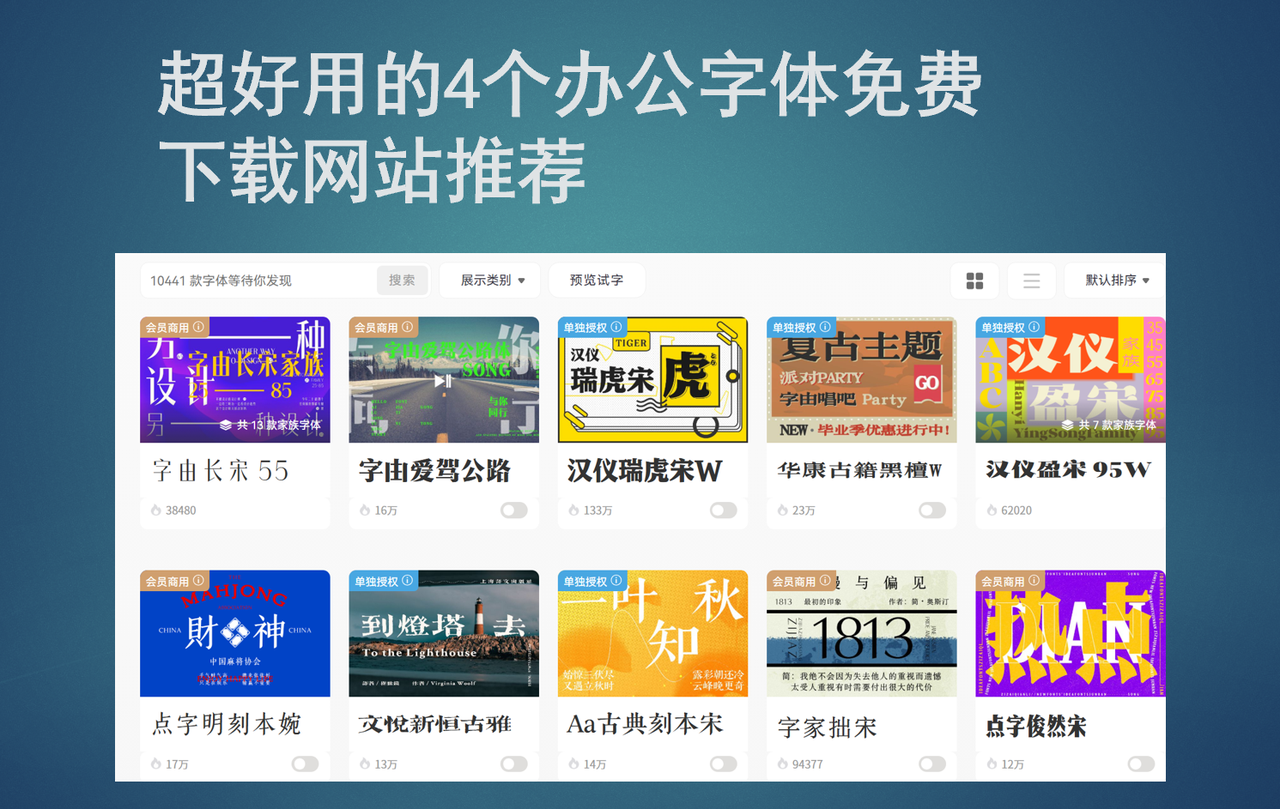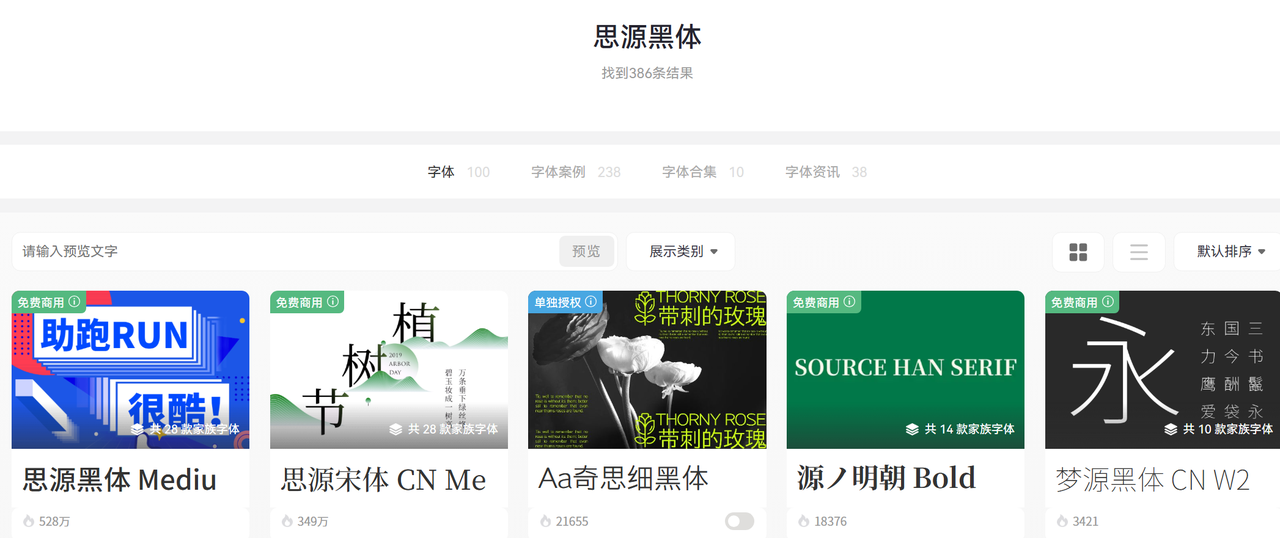
超好用的4个办公字体免费下载网站推荐
日常办公中字体的选择尤为关键,一款适配的字体能让文档、报表的呈现效果大幅提升,也能让办公表达更贴合场景需求。我一直想为大家整理靠谱的办公字体免费下载渠道,避开版权风险同时选到实用字体,本文就给大家推荐 4 个优质的办公字体免费下载网站。
一、字由网
说到办公字体下载,字由网绝对是我心中的TOP1,它不像普通网站只做简单的字体搬运,更像是办公党、设计师的“字体管家”,用起来省心又高效,一站式满足所有办公场景需求。
像是我平常用的最多的思源黑体,也是办公室同事用得最多的字体。在字由网上也是一款下载最多的办公字体,不管是敲Word长篇公文、做Excel密密麻麻的报表,还是写PPT正文,用它都特别合适。
然后是优设标题黑,我专门用来解决汇报PPT标题没亮点的问题。不管是PPT大标题,还是公司内部的活动通知标题,用它不用额外做设计,就能显得很专业,汇报质感一下子就提上来了。
最让办公党惊喜的是它的便捷性,很多免费字体网站下载后需要手动安装,换设备还要重新下载,而字由网只需下载客户端,无需繁琐安装字体文件,就能在Word、PPT、Excel等所有办公软件中一键激活使用,频繁切换字体时效率翻倍,再也不用来回切换文件夹找字体安装包。
除此之外,字由网还有很多贴合办公需求的小功能,比如AI识字的功能,遇到图片里好看的字体不知道名字,上传图片就能快速识别,直接找到同款下载;个人云字库同步功能,换电脑办公也能无缝衔接自己常用的字体,不用再手动备份。
二、猫啃网
猫啃网也是一个我经常使用的办公字体下载网站,平台有近千款优质中文办公字体能免费下载,更新频率很高,适合办公正式文档的宋体、黑体等字体在平台上大部分都是免费商用的,不用在海量字体里盲目筛选。字体下载也很便捷,点击字体详情页,就能直接下载字体文件,下载后解压安装,就能在所有办公软件中使用,适配Word、PPT、Excel等常用办公工具,对于预算有限、主打中文办公的职场人来说,绝对是性价比之选。
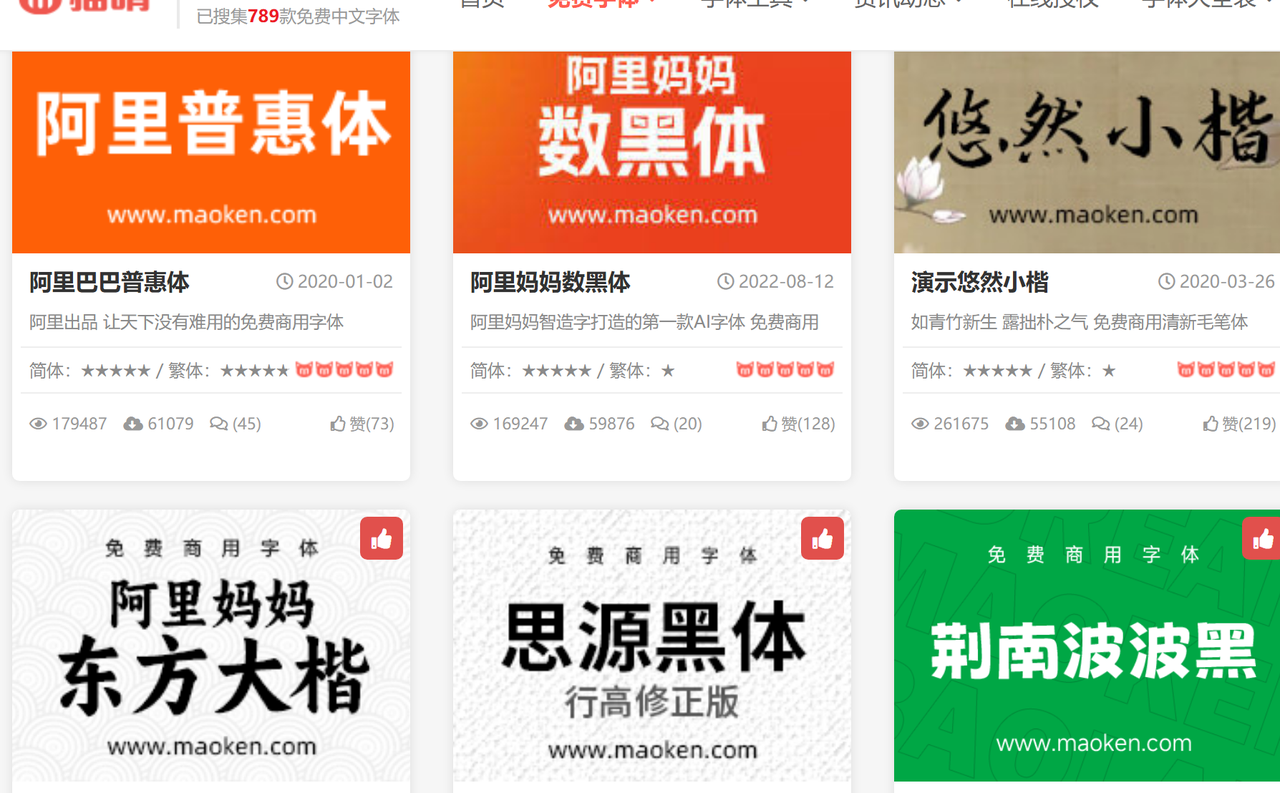
三、100font
100font是一款主打“免费商用、公益传播”的字体下载网站,网站收录了上百款优质办公字体,字体风格覆盖全面,既有适配正式公文、报表的宋体、黑体,也有适合PPT标题、活动通知的创意字体,对于职场新人、行政办公人员,或是预算有限、注重版权合规的职场人来说,100font绝对是性价比拉满的选择,用一次就能彻底爱上。
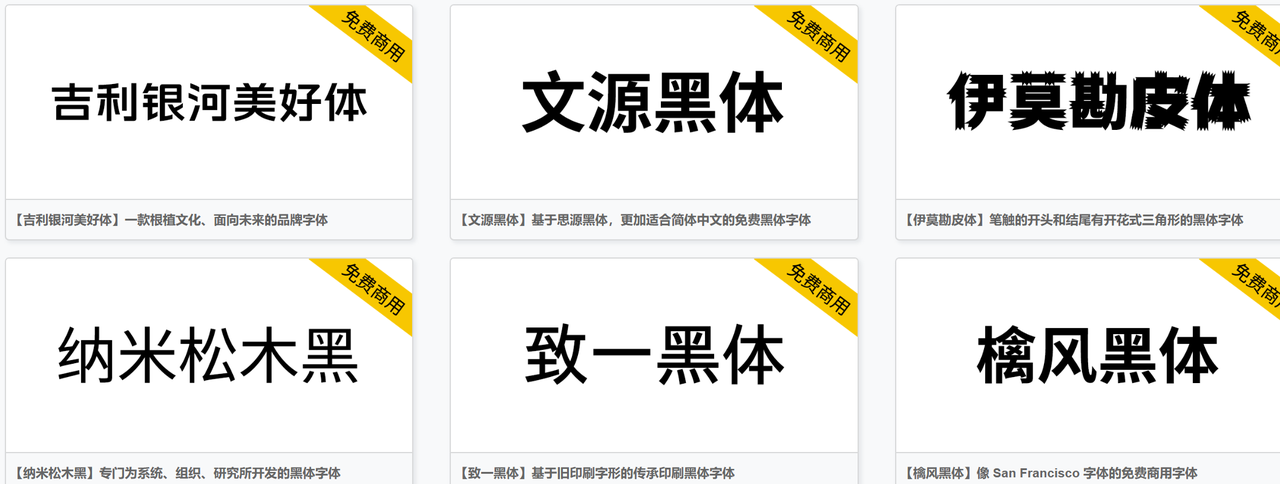
四、阿里巴巴普惠体官方下载平台
最后一个我推荐的办公字体免费下载的平台是阿里巴巴普惠体官方下载平台,这个有大厂背书的平台核心提供阿里巴巴普惠体全系列字体,既适合作为公文、报表的正文字体,也适合作为PPT标题、品牌物料的展示字体,一款字体就能通吃所有办公场景,甚至能解决生僻字无法输入的办公痛点,这是很多免费字体网站无法比拟的优势。
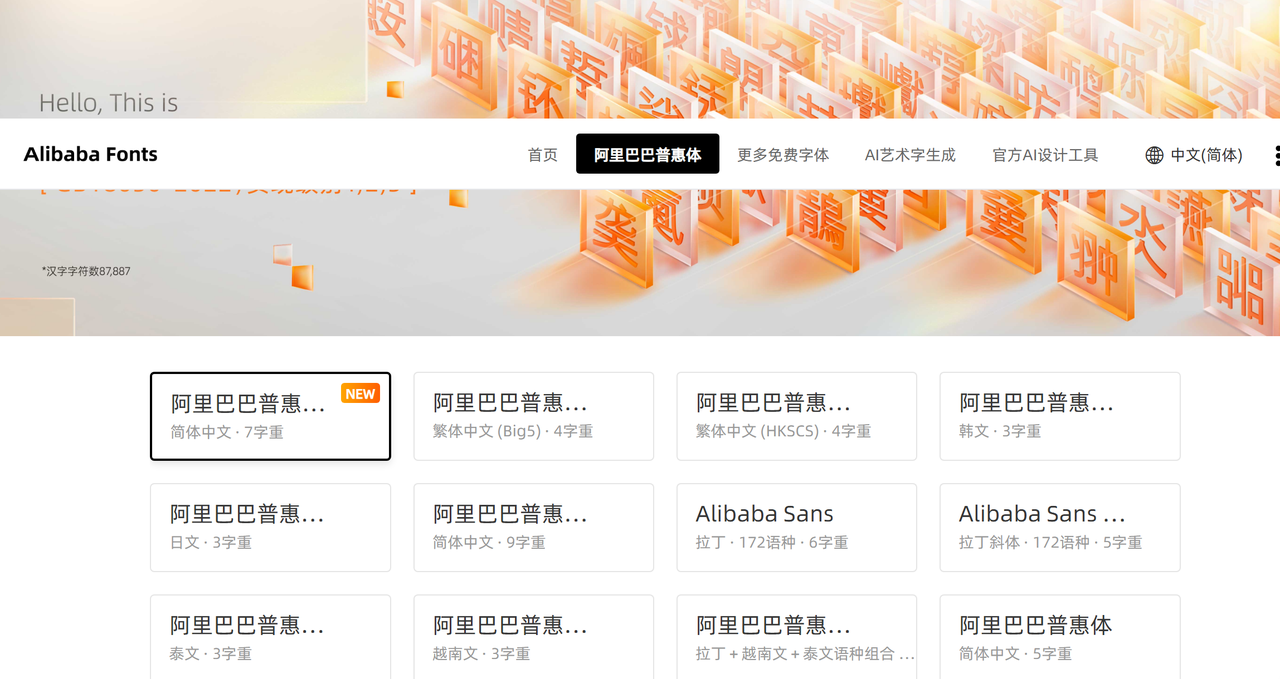
这4个办公字体免费下载网站,无论是职场新人还是资深办公党,都能找到适合自己的平台。职场办公中,一款合适的字体不仅能提升文档质感,还能体现专业态度,而这4个网站无需复杂操作,就能轻松获取各类办公字体,解决字体匮乏、侵权隐患等办公痛点。不管你是做行政办公、财务报表,还是做市场汇报、涉外文档,不管你擅长电脑操作还是新手小白,收藏这4个网站,以后找字体、下载字体,再也不用费时费力,轻松提升办公效率,让每一份办公文档都更出彩。